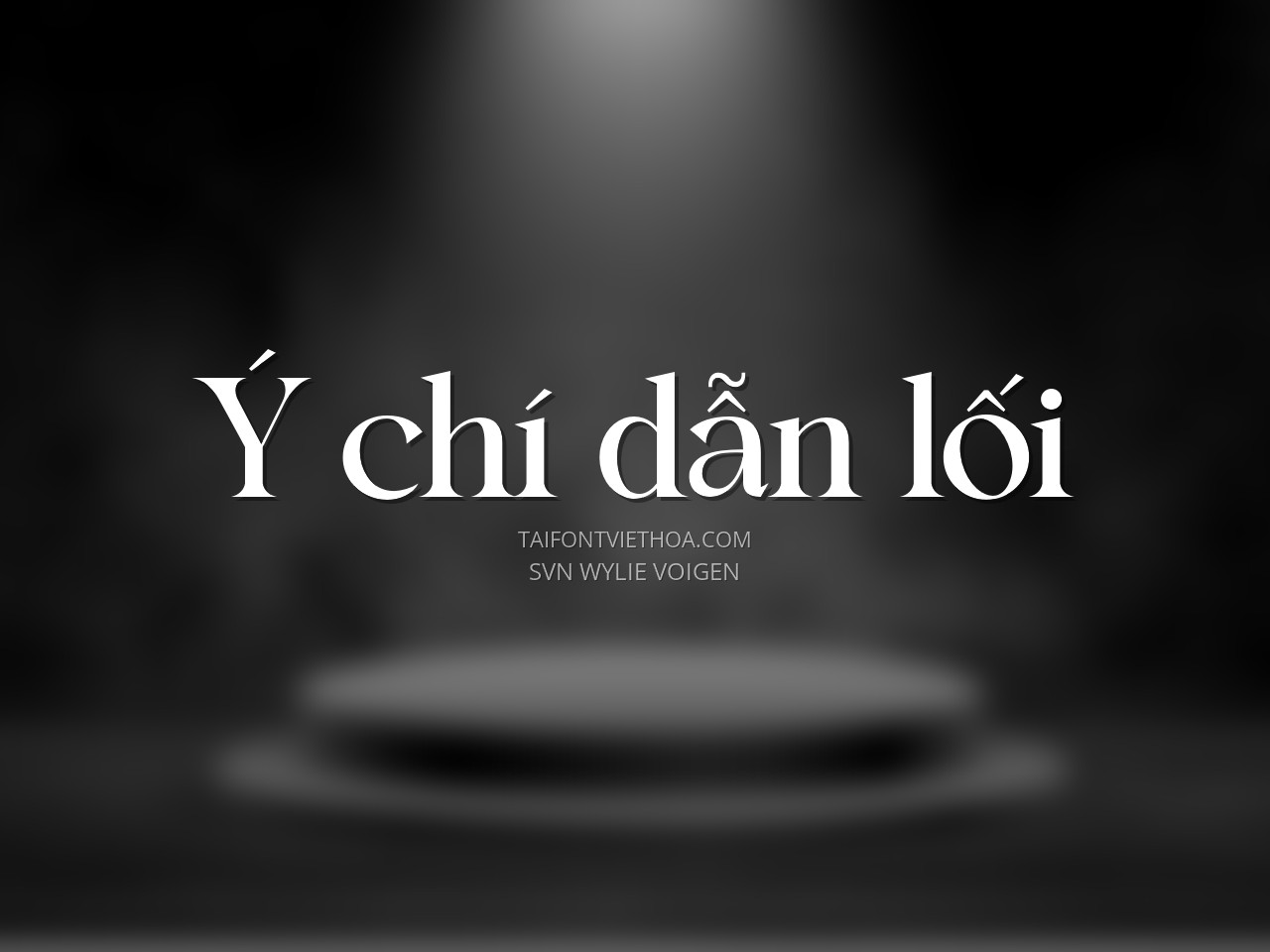
Font việt hóa SVN Wylie Voigen
Giới thiệu về font SVN Wylie Voigen – Nét cổ điển pha hiện đại cho thiết kế sang trọng
SVN Wylie Voigen là phiên bản Việt hóa của font Wylie Voigen – một kiểu chữ serif hiện đại kết hợp tinh tế giữa đường nét cổ điển và yếu tố thiết kế đương đại. Font mang trong mình cảm hứng từ các kiểu chữ in sách thời kỳ phục hưng nhưng được làm mới lại để phù hợp với xu hướng thị giác hiện nay: thanh lịch, rõ ràng, nhưng vẫn đầy cá tính. Font được sử dụng nhiều trong branding, tạp chí thời trang, và thiết kế cao cấp.
Phiên bản Việt hóa được hoàn thiện chỉnh chu bởi đội ngũ Taifontviethoa.com, hỗ trợ đầy đủ tiếng Việt và hơn 90 ngôn ngữ quốc tế khác. Font giữ nguyên tính chất sắc sảo của bản gốc, với độ tương phản cao giữa nét thanh – nét đậm, các chân chữ được thiết kế gãy gọn nhưng mềm mại. Đây là lựa chọn lý tưởng cho các nhà thiết kế muốn tạo nên thương hiệu sang trọng, thời thượng nhưng vẫn có chiều sâu nghệ thuật.
Thiết kế serif tinh tế – Ứng dụng cho thương hiệu cao cấp và thiết kế biên tập
SVN Wylie Voigen sở hữu cấu trúc serif có độ tương phản rõ rệt, khoảng cách chữ được tối ưu giúp tăng khả năng đọc ở cả tiêu đề và nội dung. Font có các đặc điểm hình học cân đối, một số glyph có đuôi cong nhẹ tạo điểm nhấn thị giác. Các ligature và ký tự thay thế được bố trí hợp lý, giúp người dùng dễ dàng sáng tạo khi dùng trong các layout mang tính nghệ thuật cao.
Ứng dụng lý tưởng: thiết kế logo cao cấp, bộ nhận diện thương hiệu, bìa sách nghệ thuật, tạp chí thời trang, danh thiếp, poster gallery hoặc bao bì mỹ phẩm. Ngành nghề phù hợp: thời trang, mỹ phẩm, nội thất, nghệ thuật thị giác, kiến trúc, truyền thông cao cấp và các thương hiệu định vị theo phong cách tối giản – sang trọng.